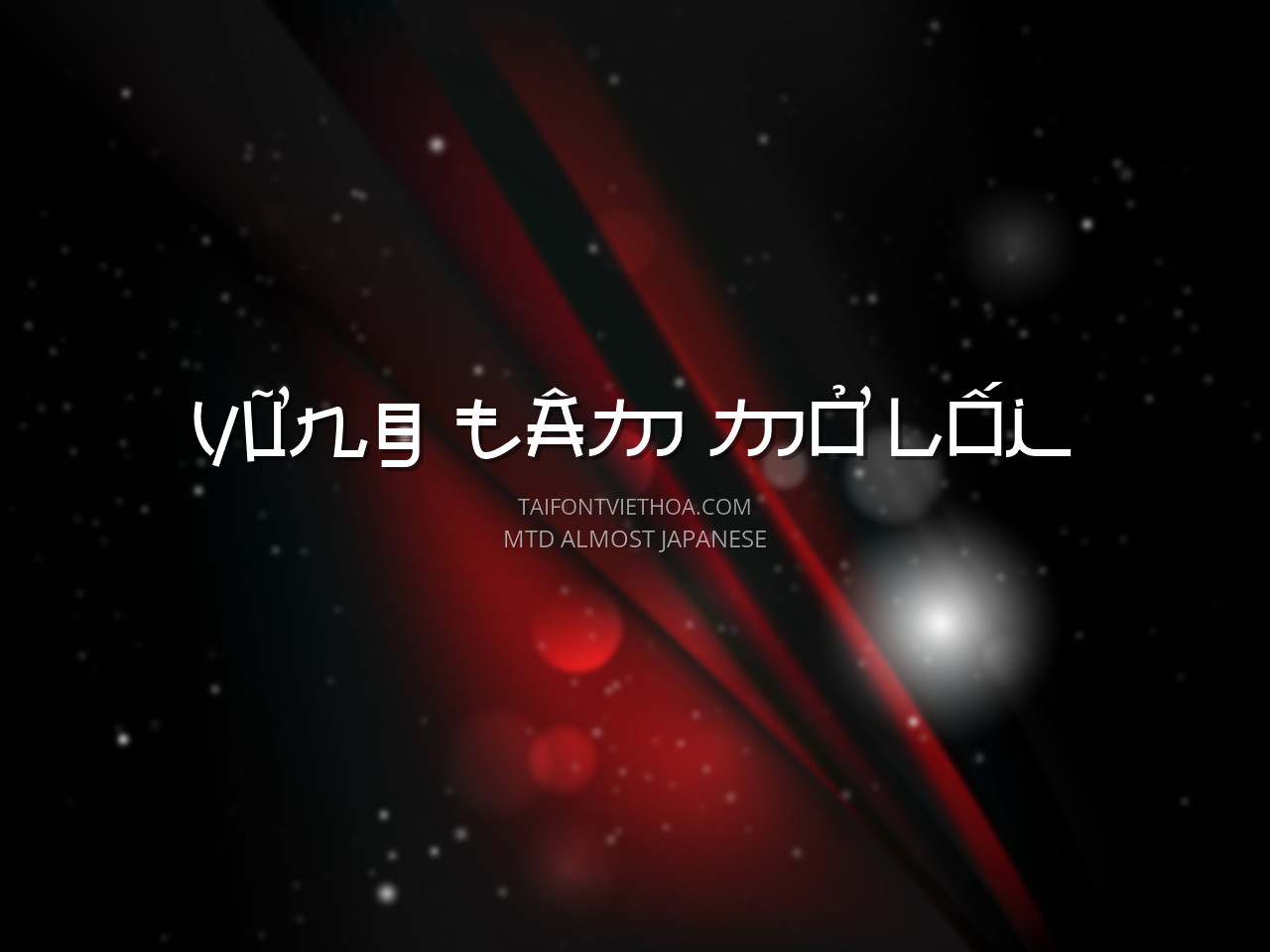
Giới thiệu về font Almost Japanese – Phong cách Nhật Bản cách điệu độc đáo và nghệ thuật
Almost Japanese là một kiểu font display độc đáo, được thiết kế theo phong cách lấy cảm hứng từ văn hóa thị giác Nhật Bản, đặc biệt là các biển hiệu truyền thống, thư pháp cách điệu và các biểu tượng cổ xưa. Font mang đậm tinh thần phương Đông hiện đại, sử dụng hình khối mạnh mẽ và đường nét gãy gọn, tạo nên một diện mạo ấn tượng, cá tính và cực kỳ thu hút thị giác.
Phiên bản Việt hóa do Mộc Hạthực hiện đã bổ sung đầy đủ hệ thống dấu tiếng Việt mà vẫn giữ nguyên các đường nét cách điệu đặc trưng. Taifontviethoa.comđã chọn lọc và giới thiệu Almost Japanese nhằm cung cấp cho cộng đồng thiết kế một font chữ mang đậm dấu ấn văn hóa Á Đông nhưng vẫn đảm bảo sự linh hoạt và thẩm mỹ cao trong ứng dụng tiếng Việt.
Đặc điểm thiết kế độc đáo và ứng dụng nổi bật của font Almost Japanese
Almost Japanese có thiết kế hình học, sử dụng các nét dày và gãy khúc, phần đuôi chữ thường cách điệu theo dạng brush thô hoặc mô phỏng các nét thư pháp. Phong cách này không chỉ truyền tải cảm hứng từ Nhật Bản mà còn thể hiện được tính nghệ thuật đương đại, rất thích hợp cho những thiết kế cần sự phá cách hoặc mang màu sắc Á Đông.
Font phù hợp để sử dụng trong: poster phim, bìa truyện tranh, thiết kế ẩm thực Nhật – Hàn, thương hiệu nhà hàng châu Á, banner sự kiện văn hóa, hoặc thiết kế bao bì mang màu sắc phương Đông. Ngành nghề lý tưởng: ẩm thực, văn hóa – du lịch, tổ chức sự kiện, nghệ thuật truyền thông, giải trí và thiết kế nhận diện thương hiệu đặc thù.